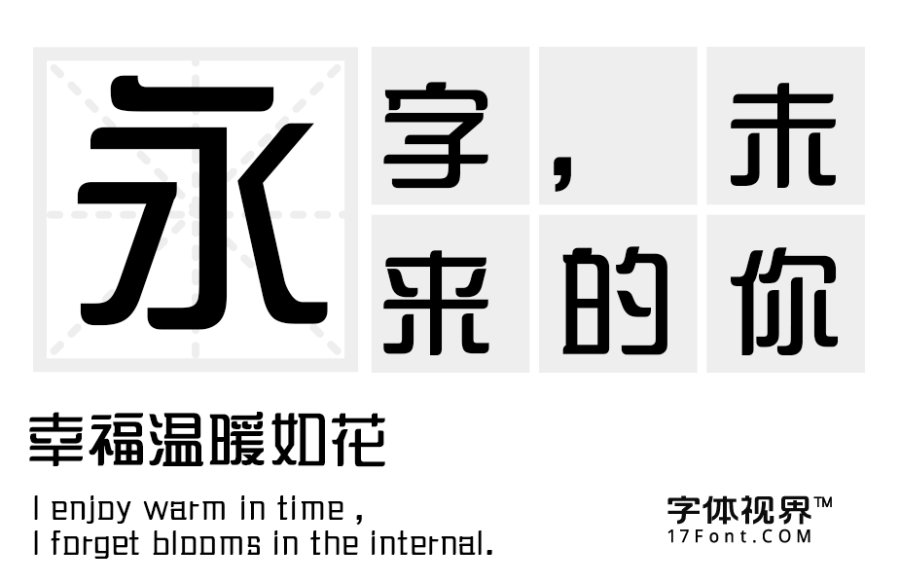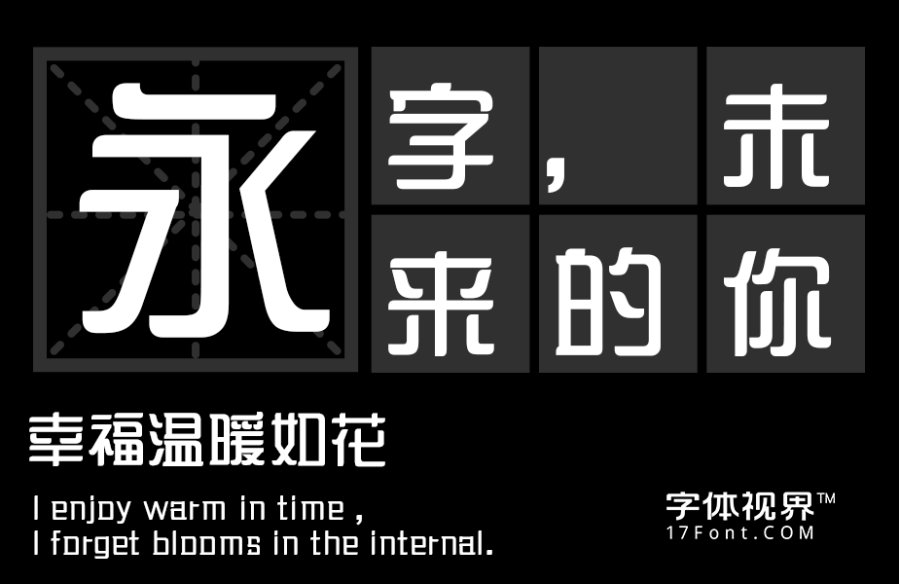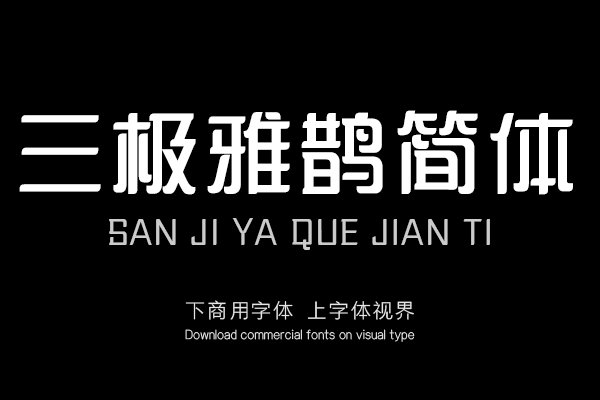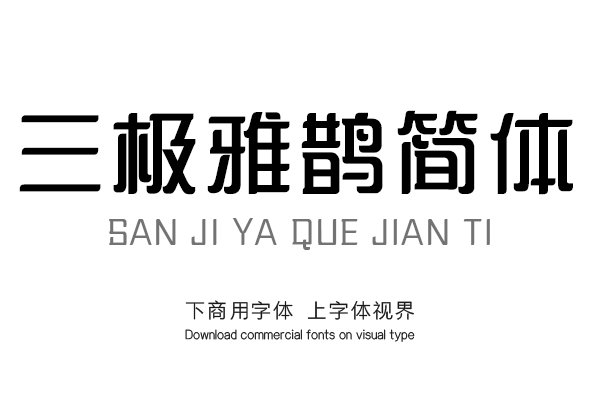
三极雅鹊简体,这款字体的起笔、收笔和转折处综合了字体与鸟类的特征,形成鹊首圆弧的字形特点,典雅灵秀,活灵活现,极富趣味感,让人不禁喜上眉梢。可广泛用于书刊、广告......购买须知:“下载服务费”与“字体VIP”所获得字体 仅用于个人非商用, 商用请联系付费授权。本字体为电脑用字,手机没有root权限不支持直接手机换字(手机如何root,请自行百度搜索教程)。购买前请先 了解清楚后再付款 ,字体为虚拟产品无法回收 一旦购买不支持退款。